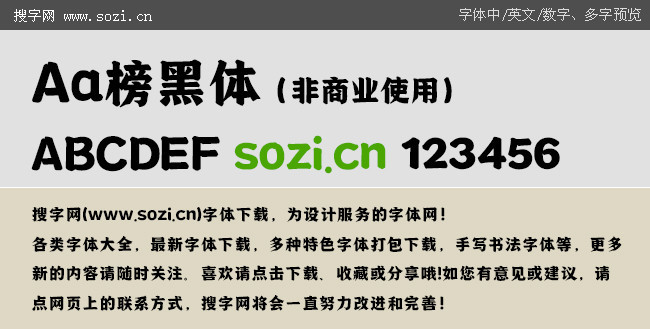
Aa榜黑體
搜字網(wǎng)給大家提供一款A(yù)a榜黑體(非商業(yè)使用)中文字體下載,該字體線條粗壯有力,風(fēng)格比一般的字體更有特色、連貫字跡顯得干練而不凌亂,清新簡(jiǎn)明,具有很好的視覺(jué)感。適合書(shū)裝設(shè)計(jì)、包裝設(shè)計(jì)、海報(bào)設(shè)計(jì)等應(yīng)用(此字體為個(gè)人非商用版,商用可以聯(lián)系QQ:1006760504)。